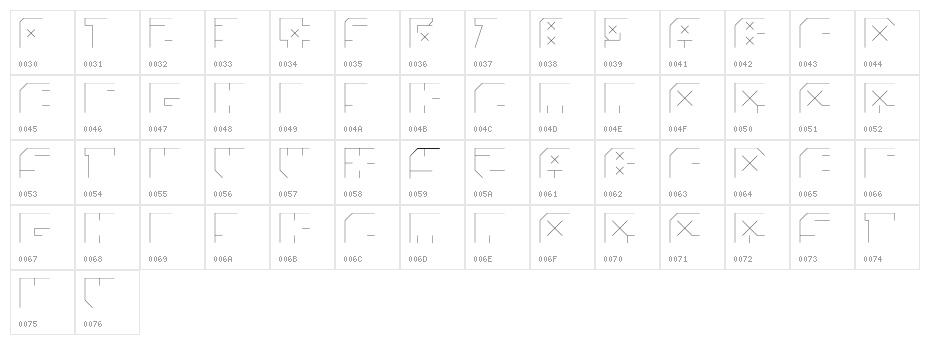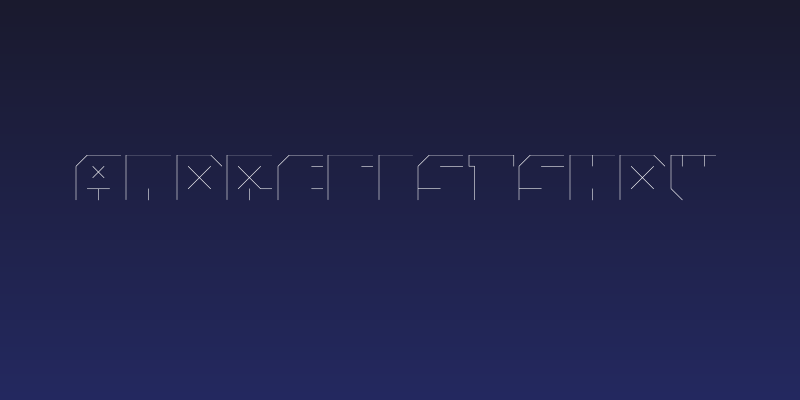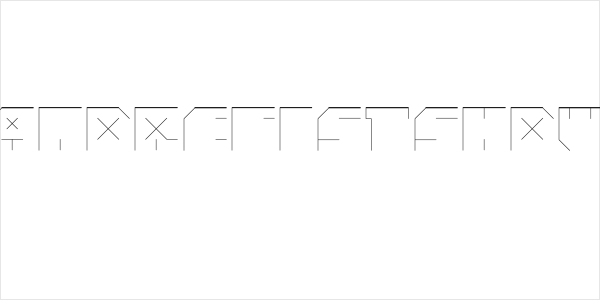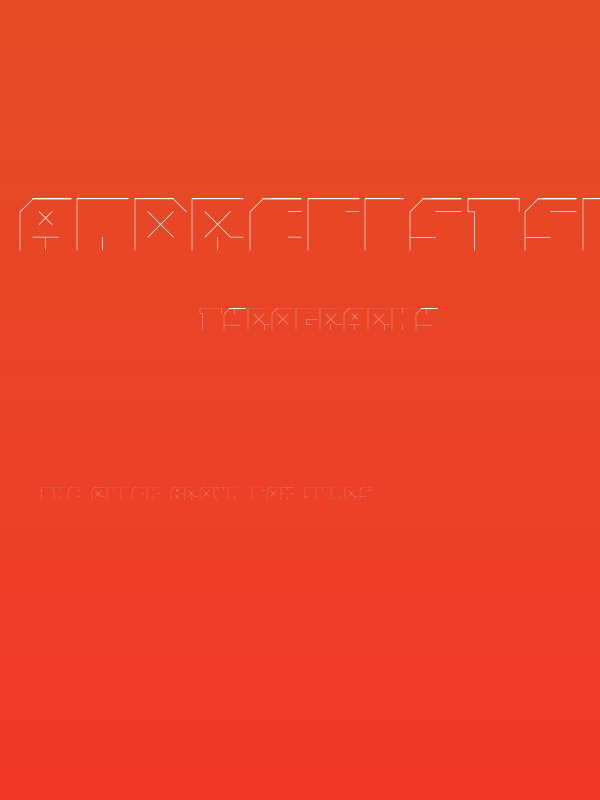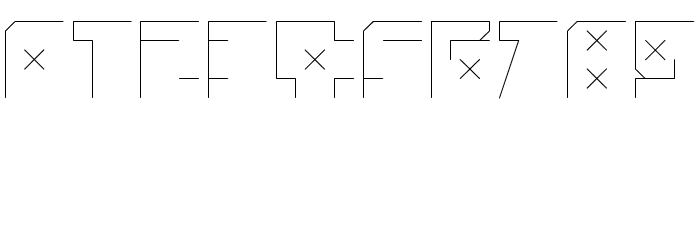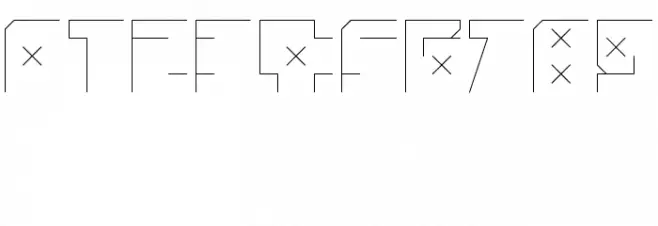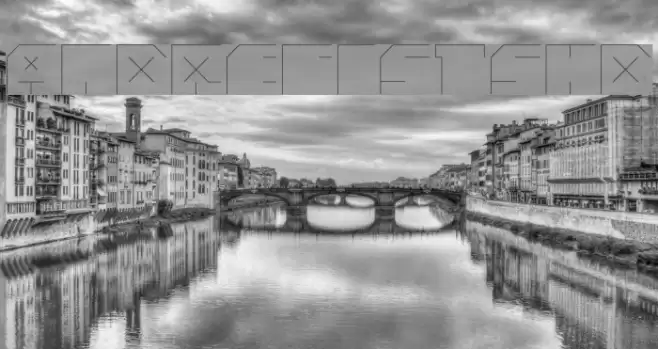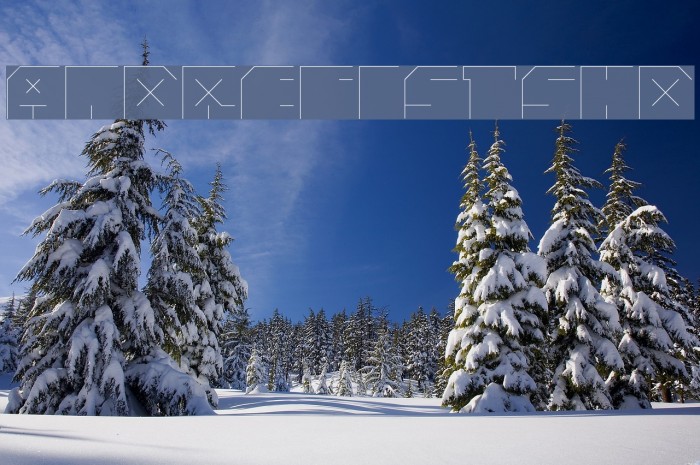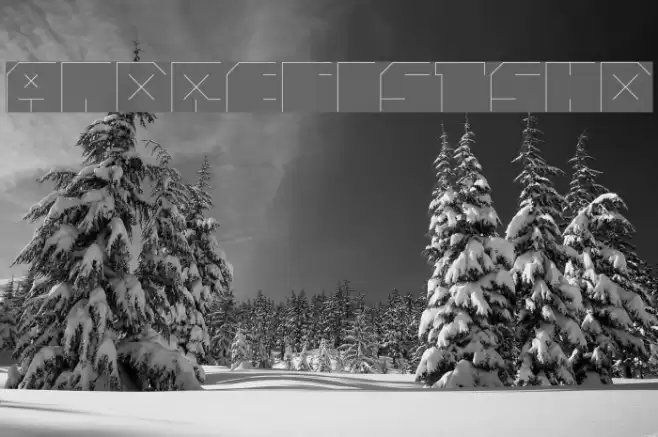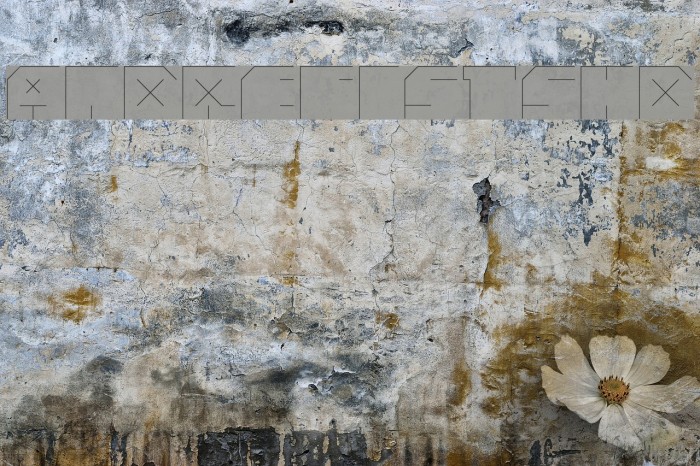
andrefistshdw Font
✎ Futuristic
| Категория | Futuristic |
| Область применения | Logos, Headlines, Digital interfaces |
| Рекомендуемые проекты | Ideal for tech-related branding, digital art projects, futuristic posters, and video game interfaces. |